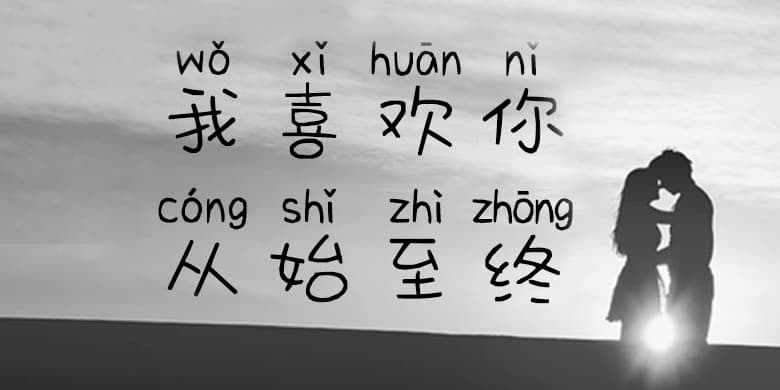
品牌:方正手迹设计师:俞亦婷发行时间:2020字库编码:大陆简体(GB2312-80)分类:创意书写字体属性:精品字
我喜欢你从始至终是一款可爱文艺兼具的手写体。该字体笔画简约纤细,分布均匀有文艺的感觉,而且因为笔画转折圆润又有了可爱的感觉。所以适用于文艺类和可爱类的书刊、品牌广告和产品包装设计,以及社交网络的个性化用字。